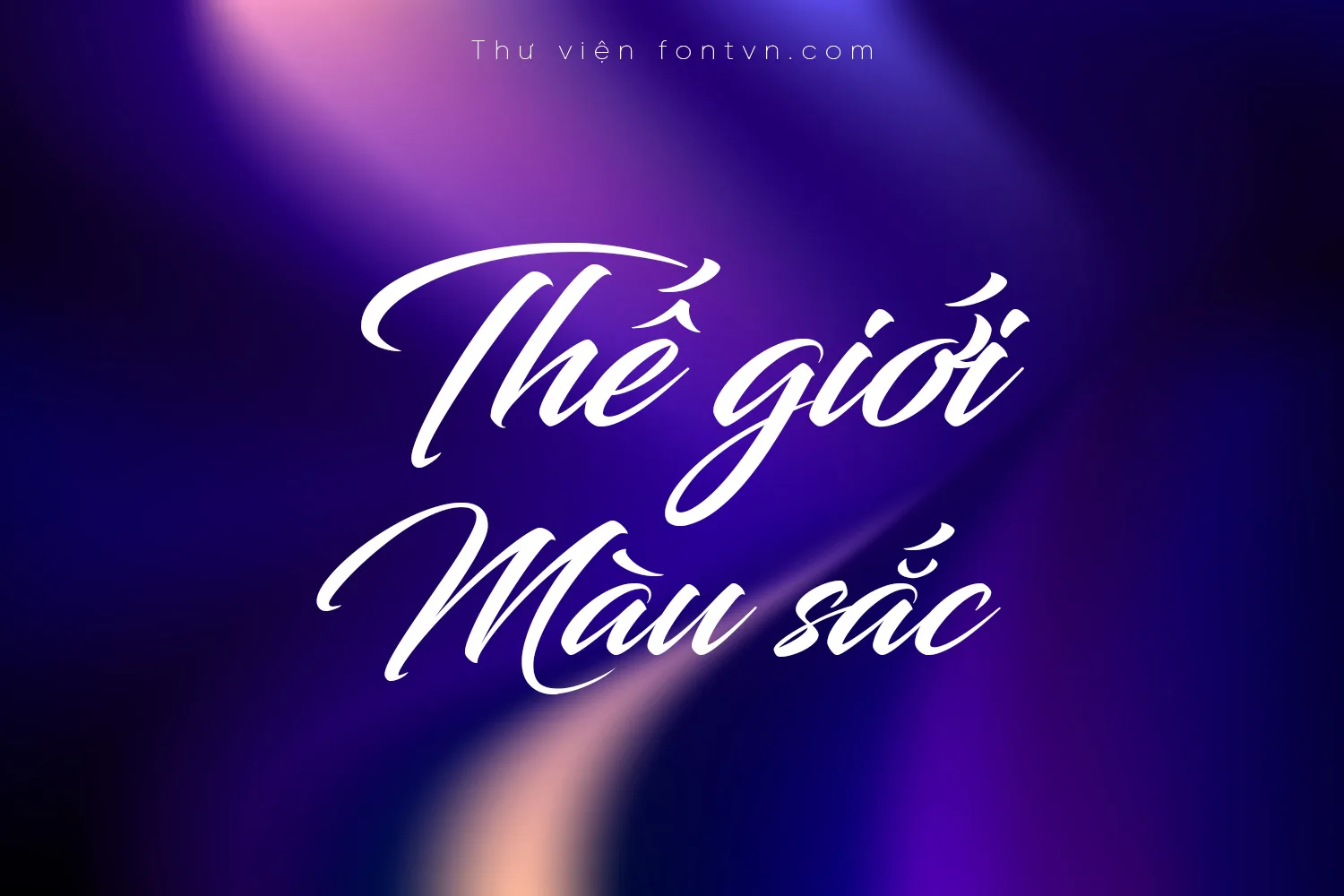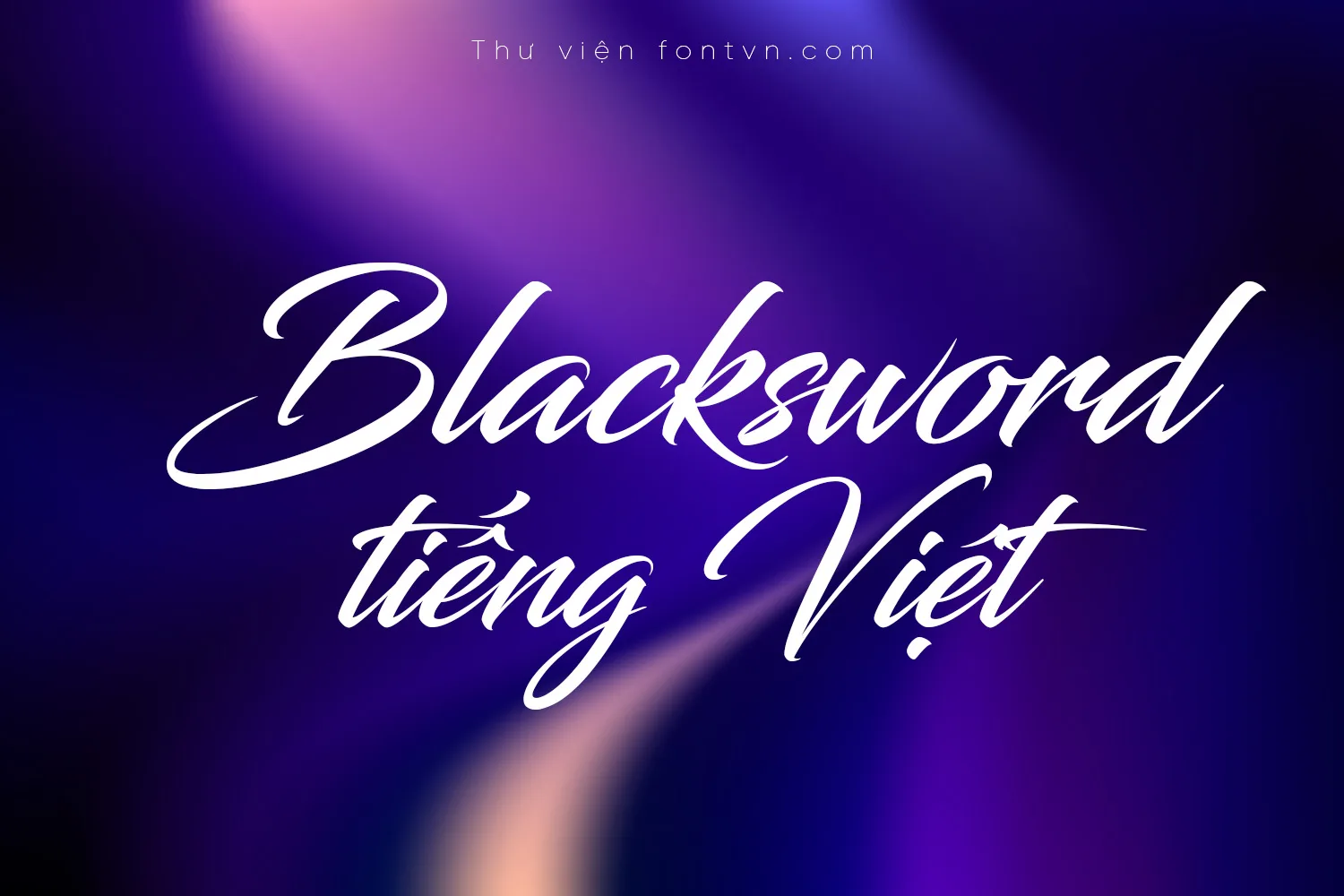
DVN Blacksword Việt hóa – Font chữ Viết Tay Bay Bổng Và Sắc Sảo
DVN Blacksword là một phông chữ dạng script (viết tay) vô cùng ấn tượng, mang đến sự kết hợp hoàn hảo giữa vẻ đẹp lãng mạn, uyển chuyển và sự mạnh mẽ, dứt khoát. Đúng như tên gọi “Blacksword”, font chữ này sở hữu những nét vuốt dài sắc bén, kết hợp cùng độ nghiêng tự nhiên tạo ra một nhịp điệu thị giác cực kỳ cuốn hút.
Phiên bản DVN Blacksword Việt hóa đã được tinh chỉnh kỹ lưỡng từng ký tự có dấu. Các dấu câu tiếng Việt được thiết kế tỉ mỉ để hòa quyện hoàn toàn với đường nét của bản gốc, đảm bảo nội dung của bạn luôn mượt mà và không bị gãy nhịp khi hiển thị.